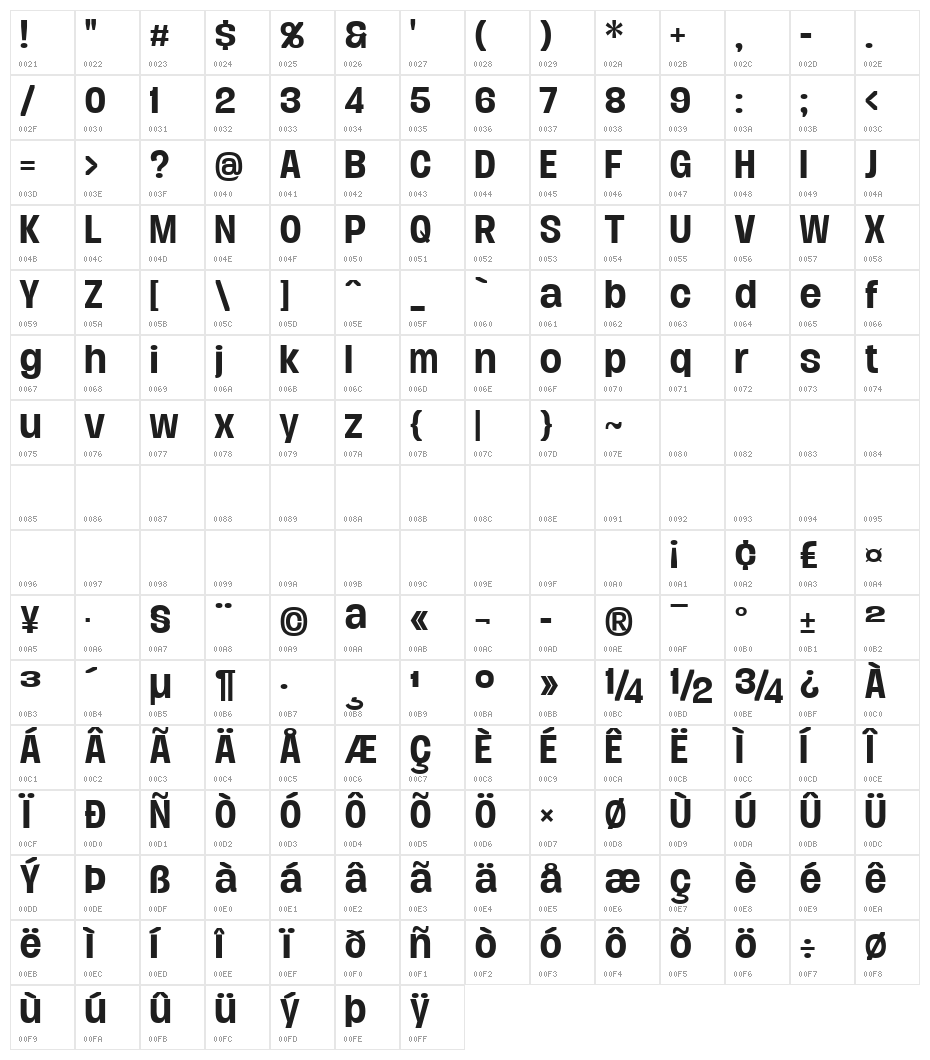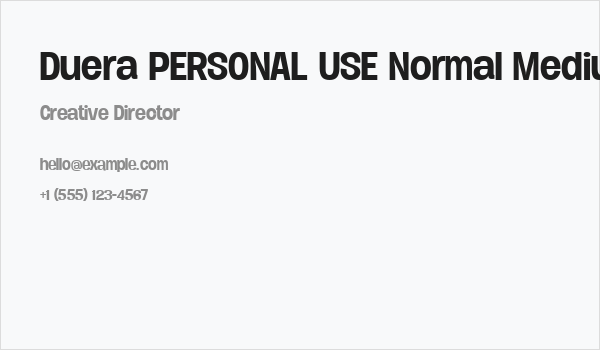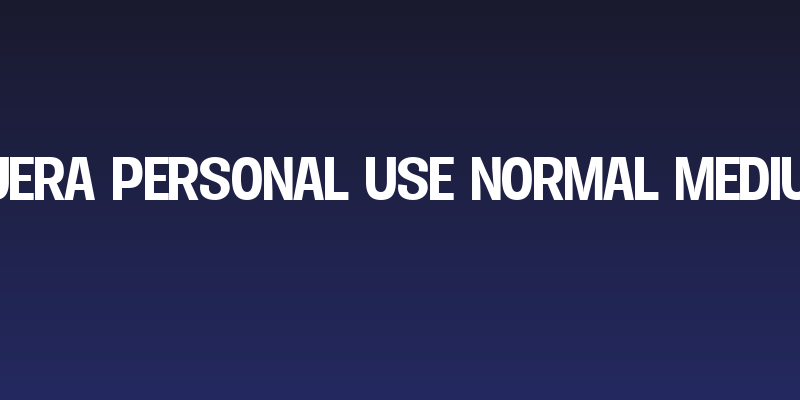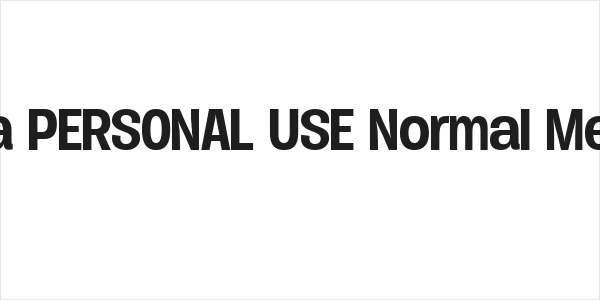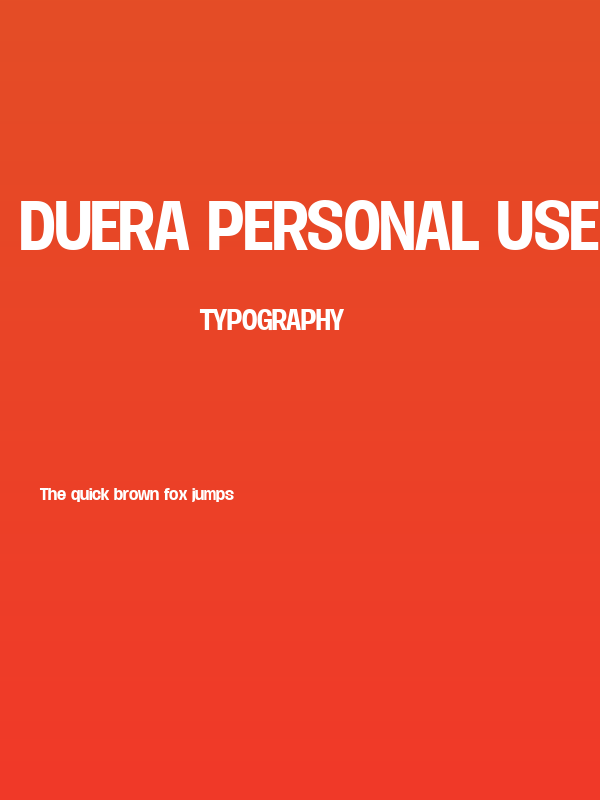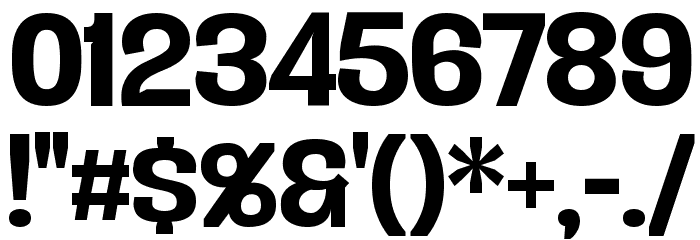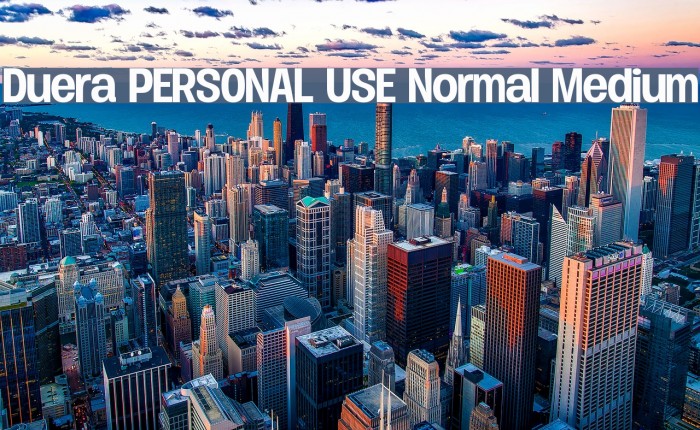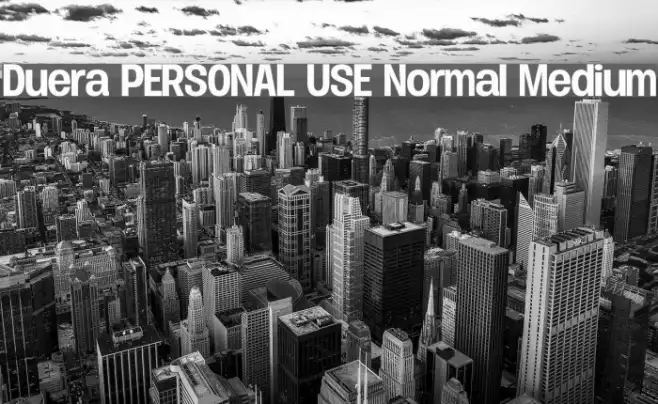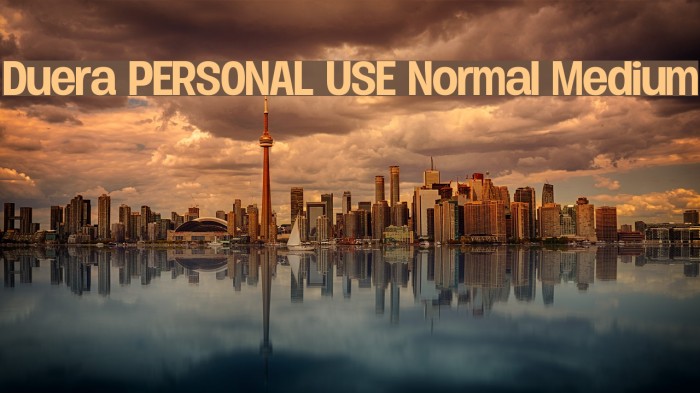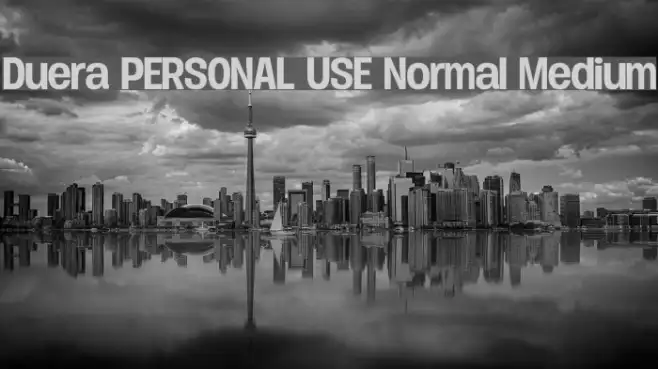
Duera PERSONAL USE Normal Medium Font
| Caso de uso | Headlines, Logos, Branding |
| Proyectos propuestos | Ideal for branding, advertising, headlines, and digital media where a strong, modern presence is desired. |